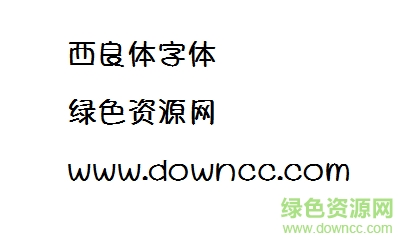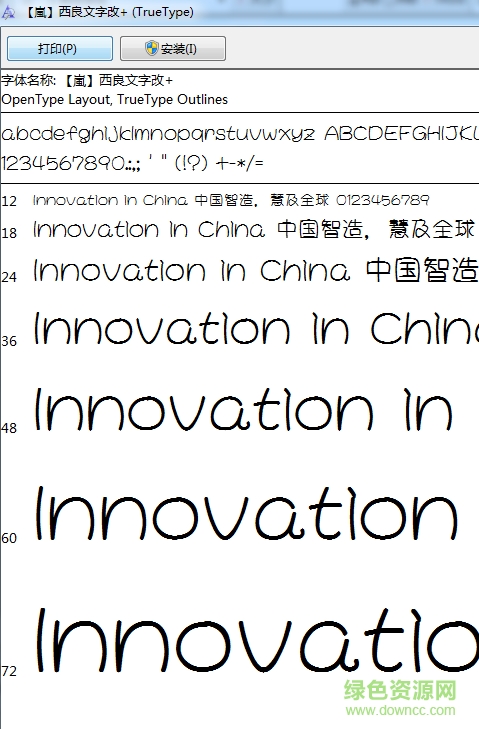
西良體是一款充滿童趣的中英文字體,該字體筆畫(huà)圓滑如流水,大字效果非常小清新,適用于廣大學(xué)子,更多好看字體盡在綠色資源網(wǎng)!
西良體字體造型生動(dòng)活潑,有鮮明的節(jié)奏韻律感,色彩豐富明快,給人以生機(jī)盎然的感受。這種個(gè)性的字體適用于兒童用品、運(yùn)動(dòng)休閑、時(shí)尚產(chǎn)品等主題。